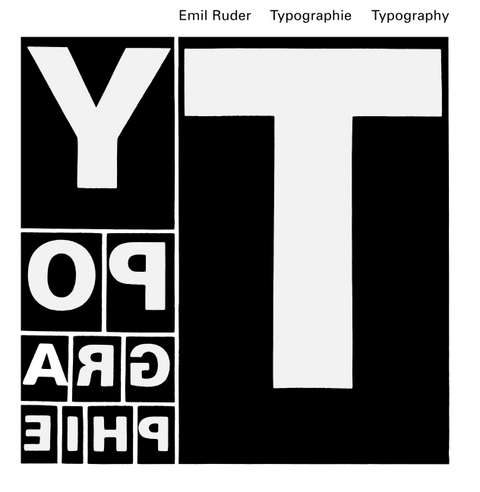
Typografie
Ein Gestaltungslehrbuch
Dieses Buch ist das Vermächtnis eines grossen Typografen an das Kulturgut der Gegenwart. In den Nachkriegsjahren, als auf fast allen Gebieten der angewandten Kunst noch kaum eine Wandlung zu einem neuen, der Zeit angepassten Ausdruck sichtbar war, liess Emil Ruder als einer der ersten Pioniere alle herkömmlichen Regeln der althergebrachten Typografie fallen und schuf neue Gesetze, die den Anforderungen an eine neue Typografie entsprachen.Bei diesem Buch, das bisher sechs Auflagen, davon einige gekürzt, erlebt hat und nun in einer Neuauflage der Originalausgabe wieder vorliegt, handelt es sich um ein grundlegend neues Lehrbuch, auf welches Generationen von Typografen und Grafikern aufbauten und weiterhin aufbauen können. Es ist bestimmt als hervorragendes 'Manual'zu werten. Darüber hinaus ist es jedoch in seinem Gesamtaufbau, in der thematischen Abwicklung, in der Gegenüberstellung von Gleichheiten und Kontrasten, im Reichtum der Bilder und der sich harmonisch einfügenden typografischen Sätze ein geschlossenes Meisterwerk. Hinter den rein pädagogischen Beispielen exakter Proportionen schimmert ein reiches philosophisches Denken hervor, welches, weit über die alltäglichen Aufgaben hinaus, die Lehre der Weisheit des Lebens zu erläutern versucht.
| Vorwort | Adrien Frutiger |